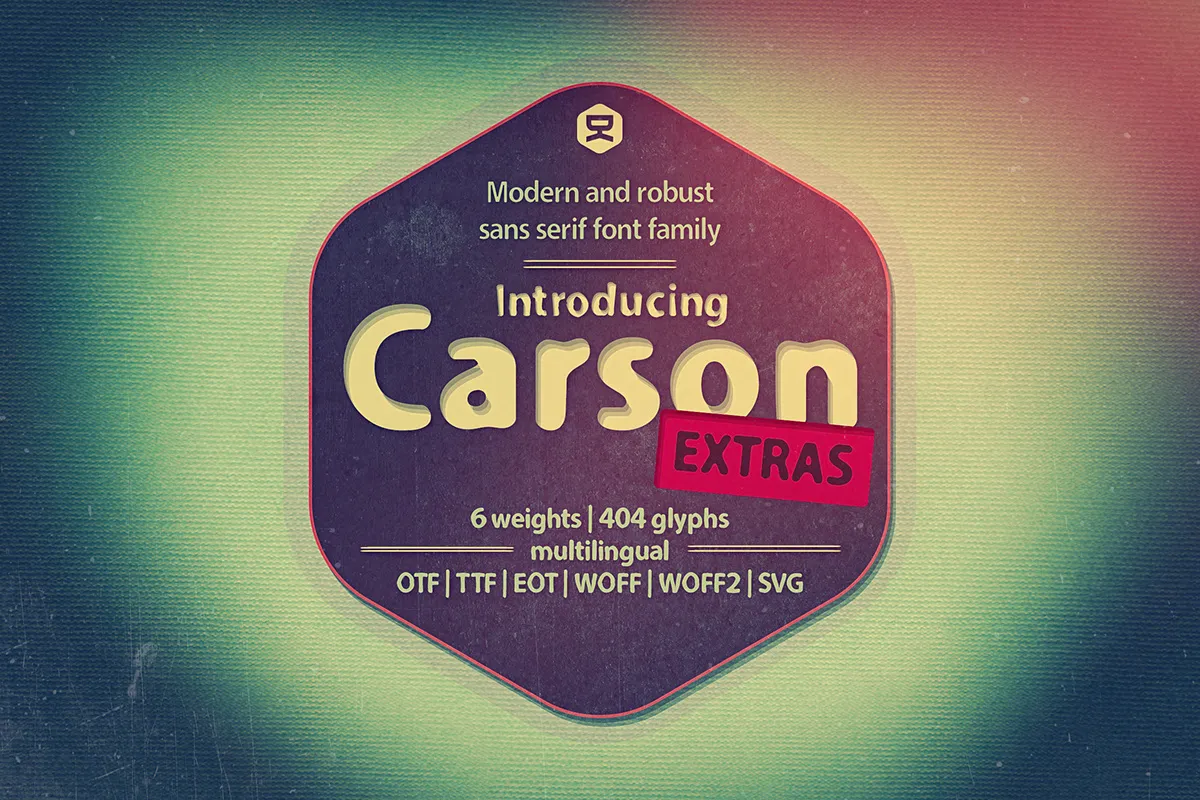
Carson Extras Typeface – Download Grátis
A Carson Extras Typeface é uma elegante fonte de linhas retas ideal para criar designs contemporâneos e sofisticados. Seu design clean e limpo oferece a tranquilidade necessária para trabalhos como cartões de visita, logotipos e materiais de marketing online. O designer Hamilton criou este tipo de fonte com uma forte base geométrica, que não só proporciona um excelente equilíbrio visual, mas também se adapta perfeitamente a diferentes tamanhos e formatos de texto. Perfeita para quem busca elegância moderna sem perder o toque personalizado, a Carson Extras oferece uma combinação única de simplicidade e riqueza em detalhes que podem tornar qualquer projeto mais atrativo e profissional. Seja você um designer gráfico ou um criador de conteúdo digital, esta fonte vai adicionar um toque único ao seu trabalho.